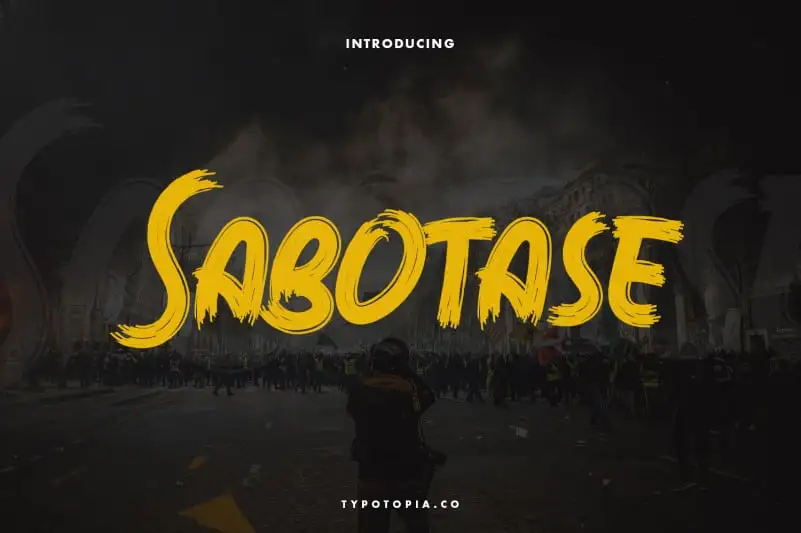
Sabotase Brush Font – Download Grátis
Introduzimos Sabotase Brush Font para uma experiência visual única que combina elegância e personalidade. Este tipo de fontes vem com duas estilos distintos que permitem criar design gráfico incrivelmente atraentes e diferentes. Sabotase Brush apresenta linhas fluidas e detalhes suaves, projetadas para destacar seus textos em ambientes digitais ou impressos. Estamos ansiosos para vê-lo incorporado em seus projetos, seja uma empresa de marketing digital ou um projeto de design gráfico pessoal. Com seu charme elegante e personalidade incisiva, Sabotase Brush é perfeito para quem busca não apenas estilo, mas também unidade visual que se destacará em qualquer ambiente. Quebre as regras com Sabotase Brush Font.